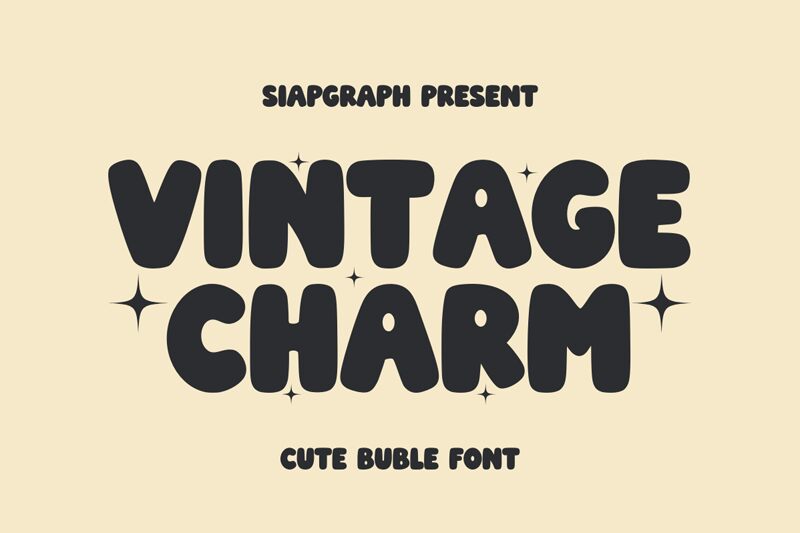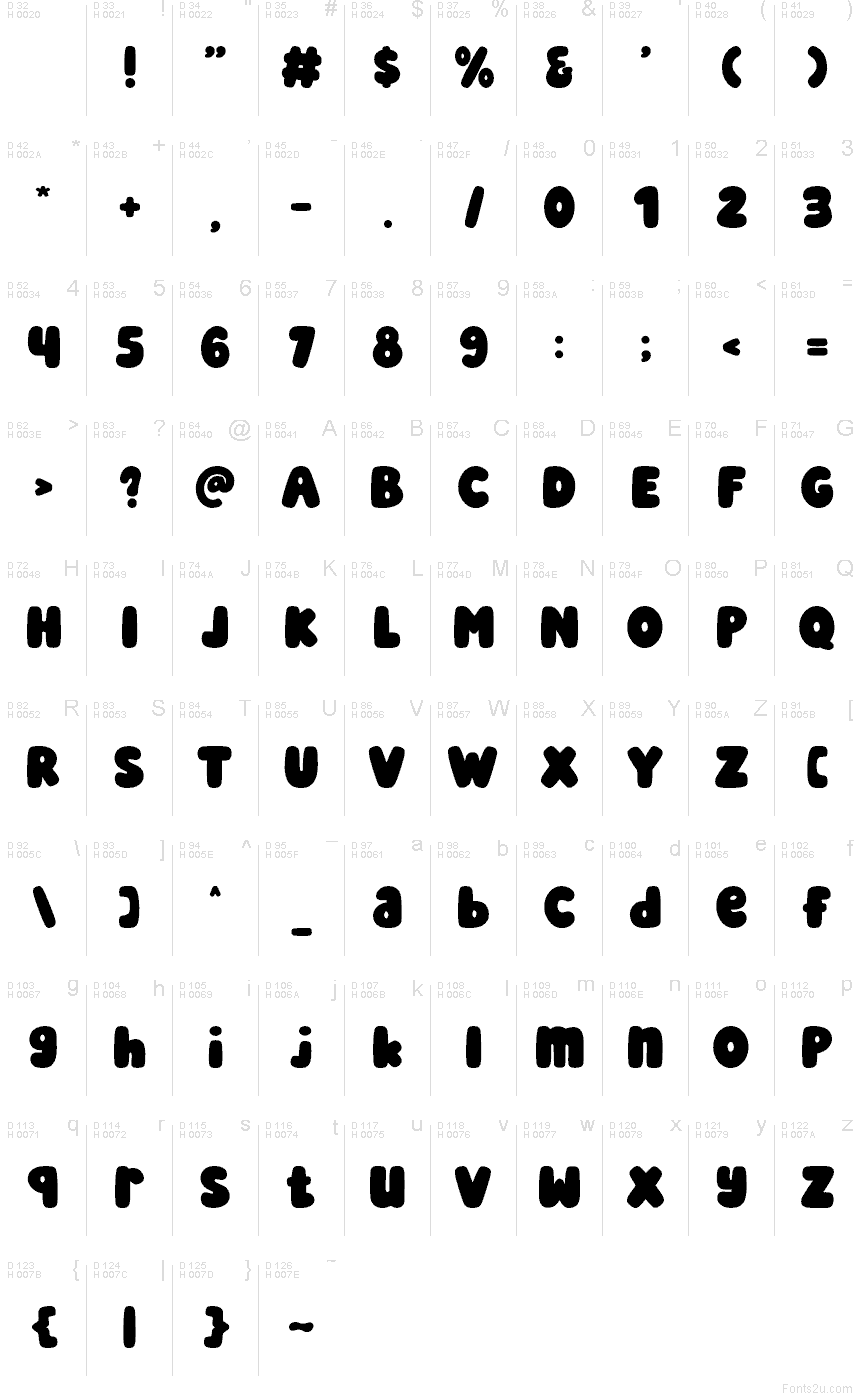
Vintage Charm
Vintage Charm от SIAPGRAPH STUDIO - это бесплатный акцидентный мультяшный шрифт, созданный на основе раздутых, скругленных силуэтов, благодаря которым буквы выглядят как мягкие вырезки из бумаги. Такой «надувной» ритм придает дизайну дружелюбный и живой характер, при этом каждый знак сохраняет достаточный вес и плавность линий, чтобы выглядеть целостно, а не просто причудливо.
Шрифт отлично подойдет для обложек детских книг, упаковки сладостей, праздничных приглашений, наклеек и забавных постов в соцсетях, где короткие слова требуют крупных, радостных форм. Широкие кривые и компактный объем придают вывескам или миниатюрам на YouTube простой, «игрушечный» шарм, не превращаясь при этом в неряшливое рукописное начертание.